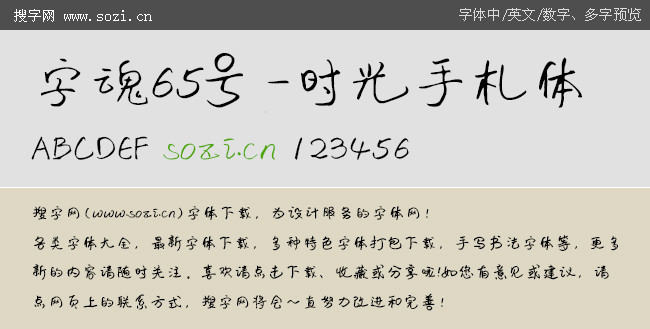
字魂65號(hào)-時(shí)光手札體
搜字網(wǎng)提供一款字魂65號(hào)-時(shí)光手札體中文字體下載,該字體是一款硬筆手寫字體,該字體包含9169個(gè)中文、字母、 符號(hào)和數(shù)字,具有古典、創(chuàng)意、有趣、童真、活潑 的風(fēng)格,可以滿足您設(shè)計(jì)上的各種需求,該字體主要用于H5、包裝、店鋪、活動(dòng)、美食餐飲 等場景。